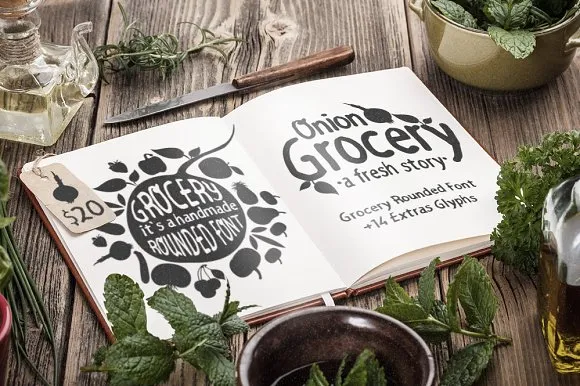
Grocery Rounded Font – Fonte Grátis
Grocery Rounded Font
A fonte Grocery Rounded é uma escolha perfeita para qualquer projeto que precise de um estilo moderno e amigável, especialmente no universo da culinária. Desenvolvida pelo designer 178-MC, esta font é uma variação do gênero sans-serif, oferecendo letras redondas para um toque mais humano em sua composição gráfica. Este design premium está disponível na Creativemarket e agora se tornou acessível gratuitamente hoje para quem deseja adquirir essa peça de arte digital. Grocery Rounded inclui todas as letras maiúsculas e minúsculas, todos os sinais de pontuação e uma incrível coleção de 14 glyphes em formato de vegetais e frutas. E o melhor é que acompanha um arquivo bonus no Adobe Illustrator, contendo logomarcas da marca Grocery. Este bônus não só adiciona um toque personalizado à sua criação, mas também permite uma integração mais profunda com seu design. Sua versão gratuita de hoje oferece um conjunto completo e detalhado que é excelente para se tornar o coração das suas criações culinárias. Seja em designs de embalagens de supermercados, identidades corporativas de restaurantes ou qualquer projeto gráfico relacionado à gastronomia, Grocery Rounded será uma escolha sólida para levar seus projetos ao próximo nível.